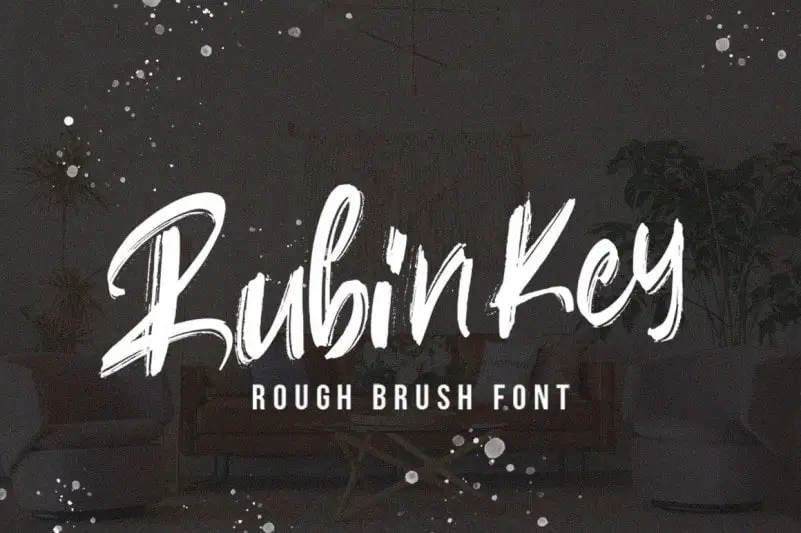
Rubin Key Brush Font – Fonte Grátis
Rubin Key Brush Font
A Rubin Key Brush Font é uma elegante fónta script moderna e ousada. Introduzida pela Vultype Co., essa fonte foi criada usando um único pen de esmalte, resultando numa fónta que transmite a autenticidade e espírito pessoal da escrita manuscrita. Ideal para estilos gráficos modernos, é perfeita para uso em elementos como marcas, produtos, músicas, roupas ou anúncios. Suas possibilidades infindáveis de aplicação tornam-a uma escolha perfeita para qualquer design que você goste de criar, seja ele um banner, logomarca ou um layout para revistas. A sua fónta é tão versátil quanto a sua criatividade. Combinada com a simplicidade e sofisticação da Rubin Key Brush Font, suas criações terão uma personalização única e moderna. Esta é uma ótima adição ao seu arsenal de ferramentas para designers que buscam algo que destaque na cena do design contemporâneo. Que tal explorar as possibilidades dessa fónta script enquanto adiciona um toque inovador a seus projetos?